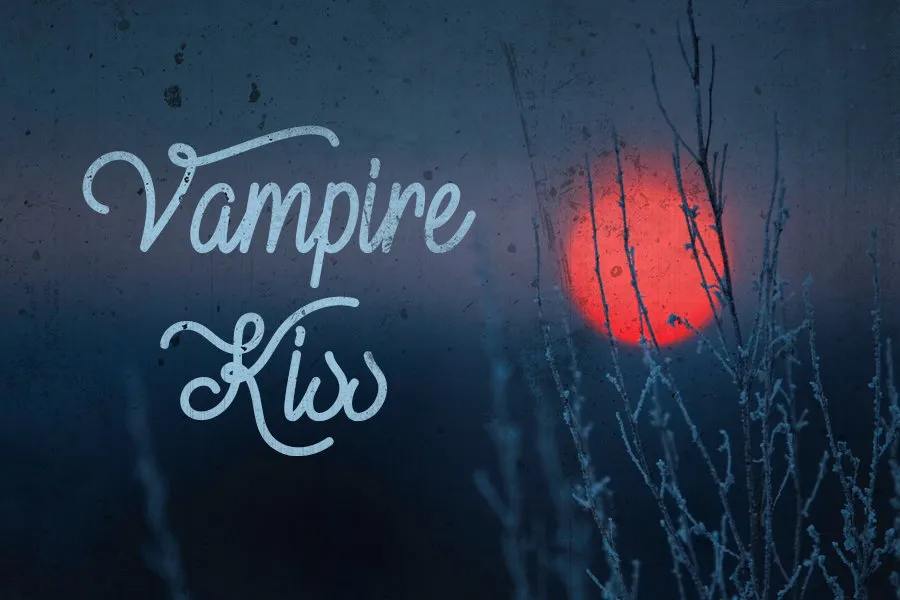
Vampire Kiss é uma fonte escrita à mão que encanta os olhos com suas linhas arredondadas e curvas suaves. Descrita originalmente como uma “fonte script”, a Vampire Kiss é perfeitamente adequada para projetos criativos onde uma trama mais elegante é desejada. Suas linhas delicadas fazem dela um ícone de elegância, especialmente quando usada em cartões de aniversário ou convites, logotipos e marcas de marca, livros fotográficos, cabeçalhos de texto ou qualquer outra maneira que você possa imaginar. A Vampire Kiss não é apenas uma escolha de fonte para criar designs únicos, mas também um recurso visual fascinante em sua própria direção. Com Vampire Kiss à mão, a personalização e o estilo são facilmente incorporados em diversos projetos gráficos.